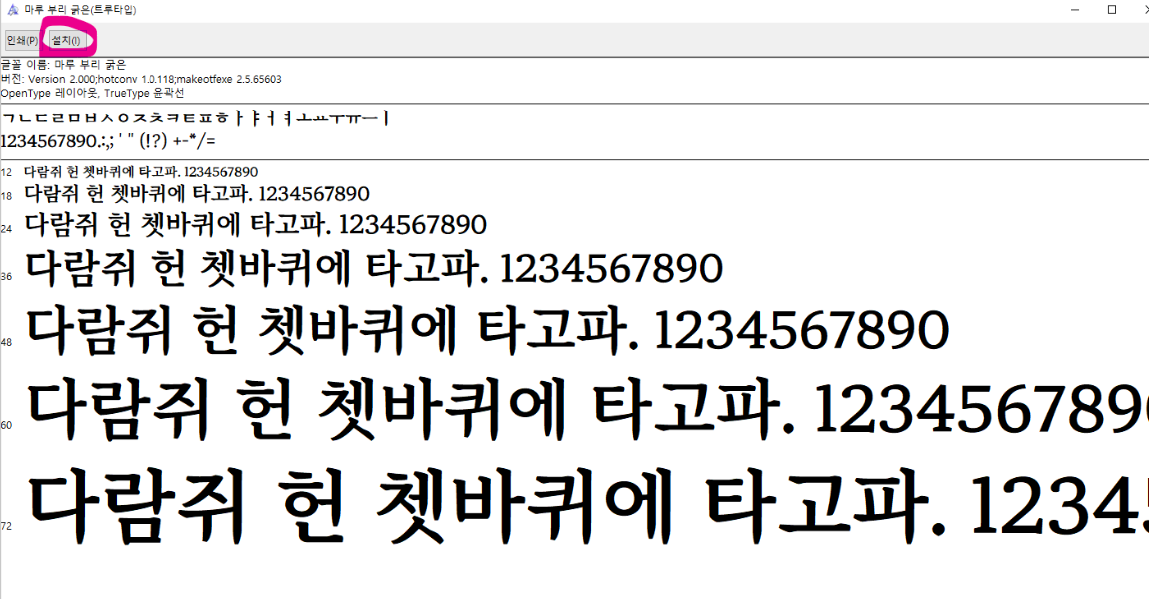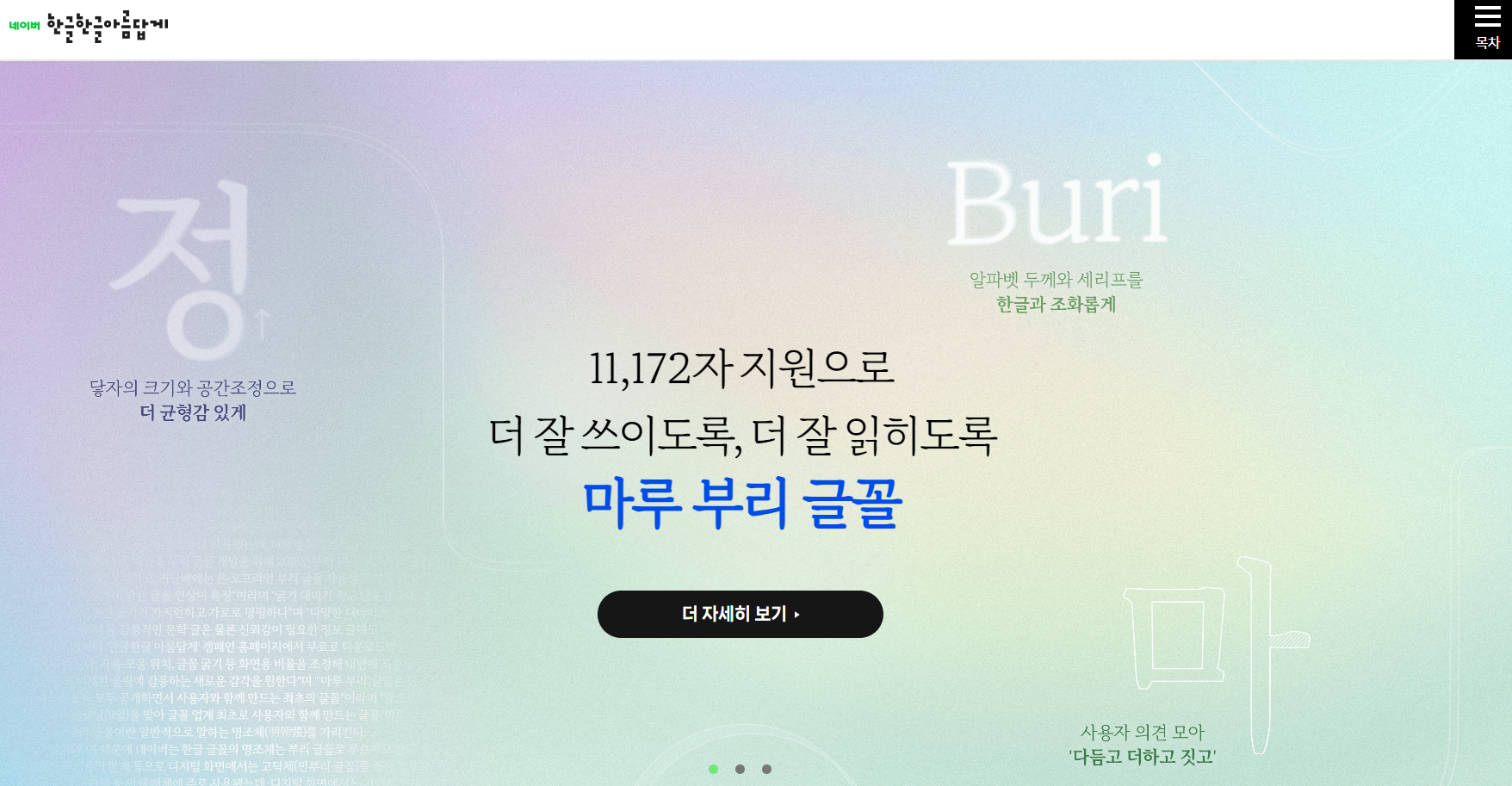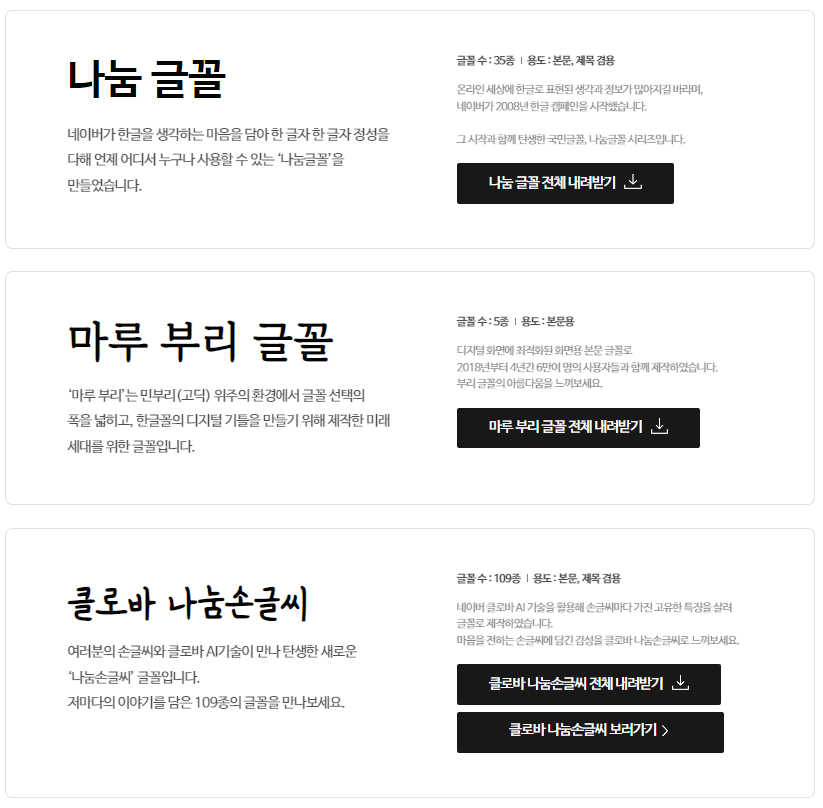
네이버 무료 폰트 소개
네이버는 개인 및 기업 사용자를 위해 다양한 무료 폰트를 제공하고 있습니다.
대표적인 네이버 무료 폰트
나눔글꼴: 네이버에서 직접 제작한 대표적인 무료 폰트로, 고딕, 명조, 손글씨 등 다양한 종류가 있습니다.
- 나눔고딕: 가장 많이 사용되는 네이버 무료 폰트로, 가독성과 균형이 뛰어나 웹, 디자인, 문서 등 다양한 용도로 활용됩니다.
- 나눔명조: 부드럽고 우아한 느낌으로, 서적, 보고서, 편지 등 인쇄물에 적합합니다.
- 나눔손글씨: 자연스럽고 친근한 느낌으로, 웹사이트, 디자인, 개인 콘텐츠 등에 활용됩니다.
마루 부리 글꼴: 네이버에서 출시한 오픈 소스 폰트로, 전통적인 한글 글꼴의 아름다움을 현대적인 감각으로 재해석한 글꼴입니다.
- 마루 부리 고딕: 굵고 든든한 느낌으로, 제목, 광고, 포스터 등에 적합합니다.
- 마루 부리 명조: 부드럽고 우아한 느낌으로, 책, 잡지, 웹사이트 등에 활용됩니다.
클로바 나눔손글씨: 네이버 인공지능 플랫폼 클로바에서 개발한 손글씨 폰트로, 다양한 필체와 스타일을 제공합니다.
- 클로바 나눔손글씨 가람연꽃: 가녀럽고 우아한 필체로, 일기, 메모, 디자인 등에 활용됩니다.
- 클로바 나눔손글씨 갈맷글: 굵고 낙서 같은 느낌으로, 포스터, 배너, 그래픽 디자인 등에 적합합니다.
네이버 무료 폰트는 다양한 종류와 뛰어난 품질로 개인 및 기업 사용자들에게 인기가 높습니다.